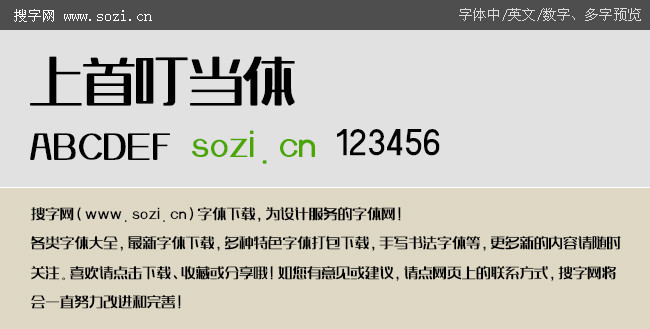
上首叮當(dāng)體
搜字網(wǎng)給大家提供一款上首叮當(dāng)體中文字體下載,上首叮當(dāng)體,字體風(fēng)格方正,字體筆畫(huà)豎勾、豎折都做了簡(jiǎn)化的處理。字庫(kù)整體特征堅(jiān)硬、有力,具有現(xiàn)代、國(guó)際化的指向性,適用于搭配標(biāo)志、廣告標(biāo)語(yǔ)、商業(yè)廣告等高端屬性。